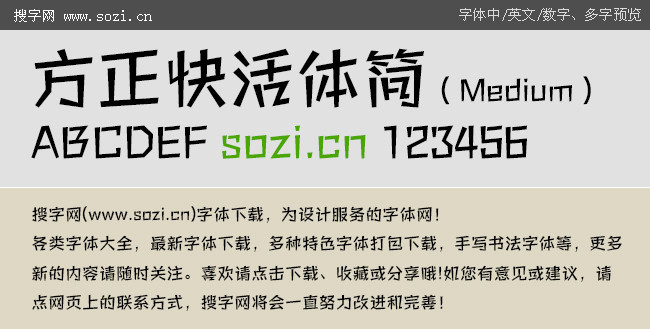
方正快活體簡(jiǎn)Medium
搜字網(wǎng)提供一款方正快活體簡(jiǎn)中文字體下載,方正快活體的創(chuàng)作靈感來(lái)源于換牙時(shí)期缺少牙齒的孩童,雖然缺少了牙齒,卻仍然笑容燦爛?旎铙w的“口”形用缺了下劃來(lái)表達(dá)特色,形成底部開(kāi)口(笑容)的布局,充滿趣味性,大膽創(chuàng)新。但又不會(huì)失去字體原來(lái)的寫法,一看便知什么字,非常適合兒童,年輕人品牌,飲料,礦泉水和餅店的廣告宣傳和包裝設(shè)計(jì)。